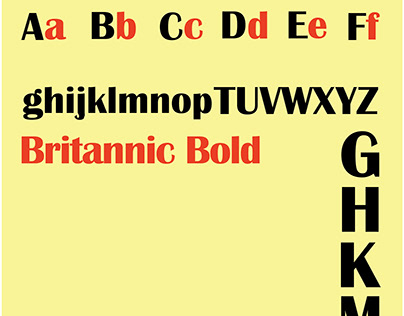
Font Britannic Bold
Ngày phát hành: 1901
Phân loại: Cổ Điển
Độ dày: Bold
Nếu bạn đang tìm kiếm một font chữ độc đáo và nổi bật để sử dụng trong các dự án thiết kế, Font Britannic Bold là một lựa chọn tuyệt vời. Được biết đến với phong cách đậm nét và thanh lịch, Font chữ không chân này thường được sử dụng trong các tiêu đề, logo, và các tài liệu quảng cáo để tạo sự ấn tượng mạnh mẽ. Với đường nét rõ ràng và sắc sảo, Britannic Bold không chỉ giúp làm nổi bật nội dung mà còn tạo nên sự chuyên nghiệp và đẳng cấp cho bất kỳ thiết kế nào.